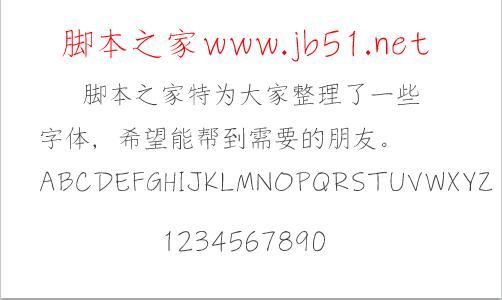
孫樹(shù)徽手寫(xiě)體ABC字體是一款硬筆手寫(xiě)體字體,字體很細(xì),給人的感覺(jué)很清爽,適合應(yīng)用于藝術(shù)設(shè)計(jì)、平面宣傳設(shè)計(jì)、網(wǎng)頁(yè)設(shè)計(jì)、書(shū)法字體,海報(bào)設(shè)計(jì)等領(lǐng)域。歡迎喜歡這款字體的朋友下載收藏。